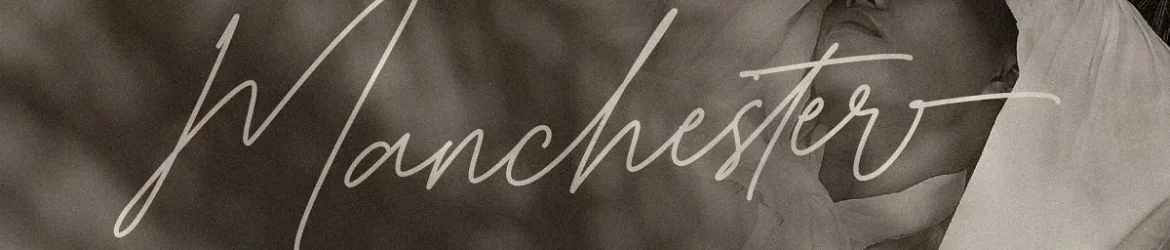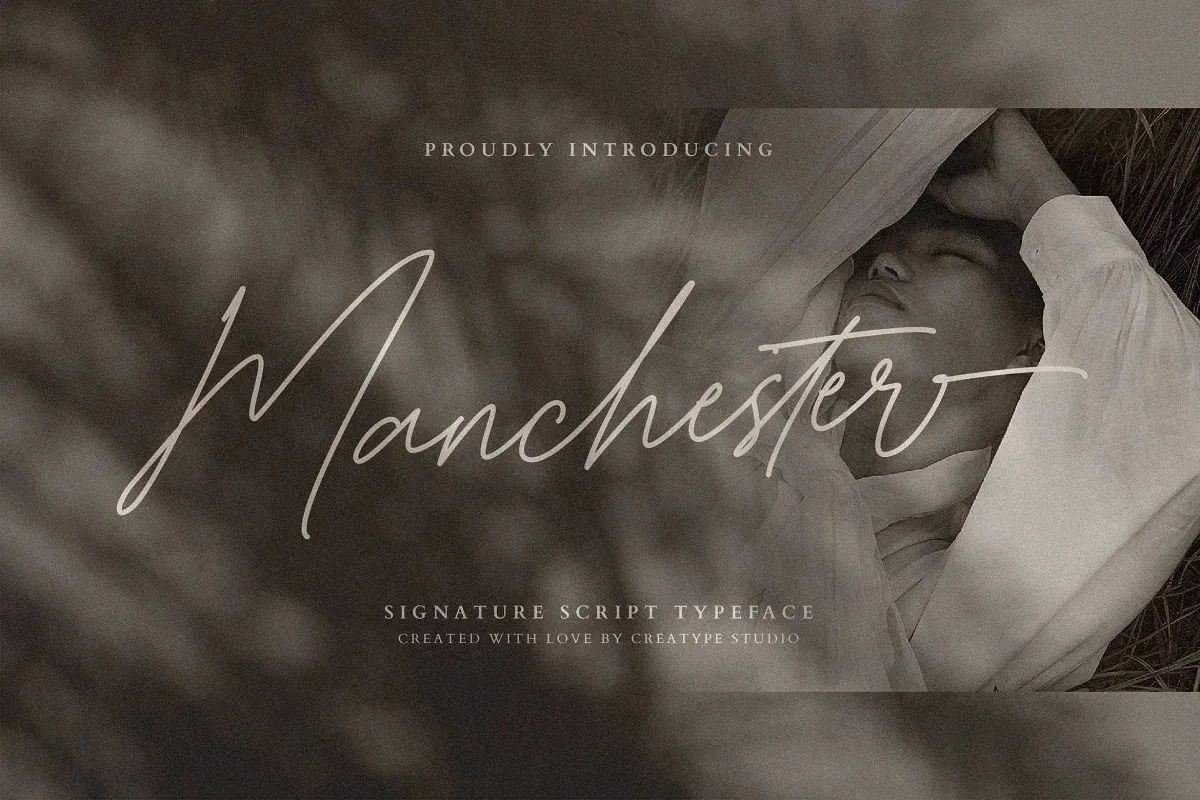
Manchester Font – Fonte Grátis
Manchester Font
Esta é uma bela tipografia assinatura criada pelo Creatype Studio com uma pequena pitada elegante. Esta fonte foi cuidadosamente projetada para textos escritos a mão, e oferece 18 ligaturas e 25 alternativas para garantir linhas fluidas e espontâneas. Manchester Font é perfeito para incorporar um toque único em aplicações que exigem autenticidade natural no design do texto. Seja você designer de sites, publicitário ou gráfico, essa fonte será uma excelente adição a sua biblioteca de recursos digitais. Com sua elegância sofisticada e seu compromisso com o texto de escrita manual livre, Manchester Font certamente trará um toque autêntico ao seu trabalho.